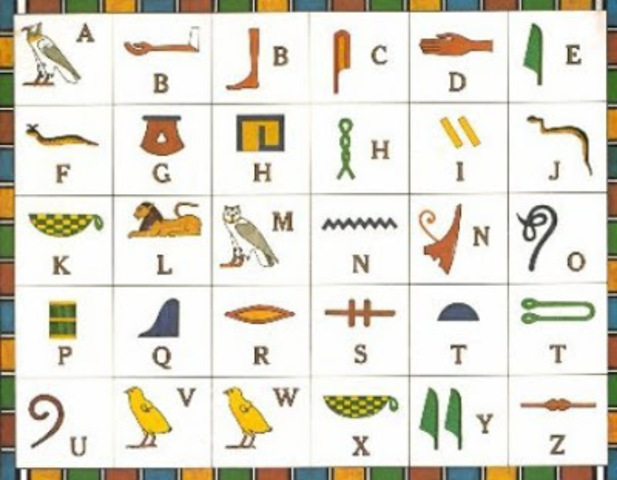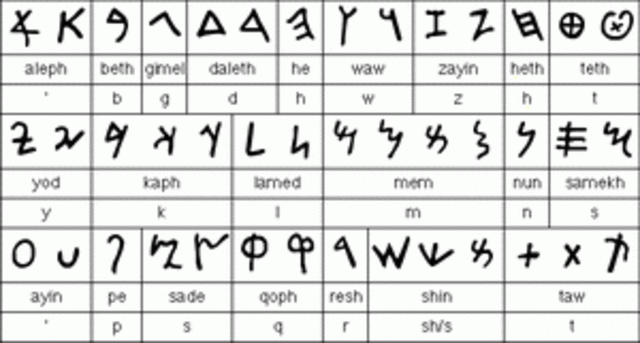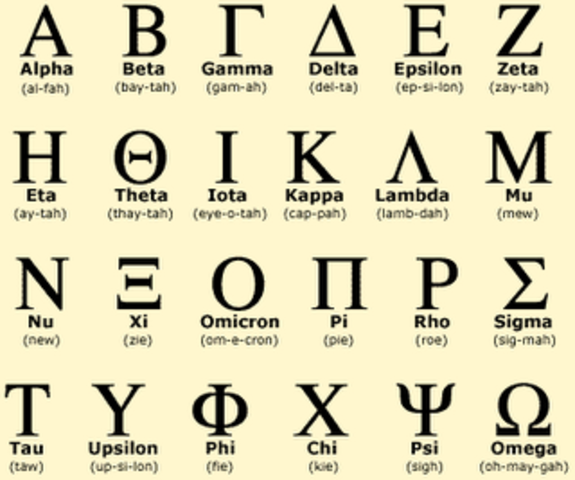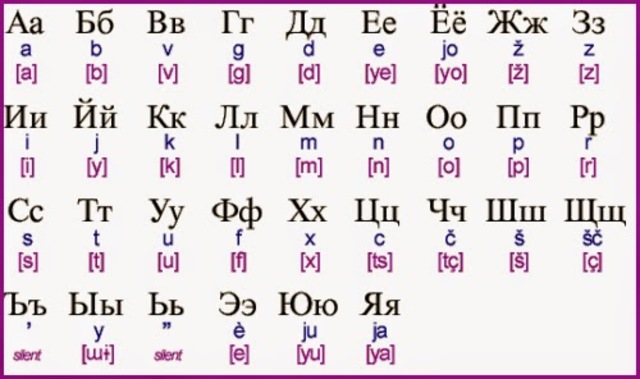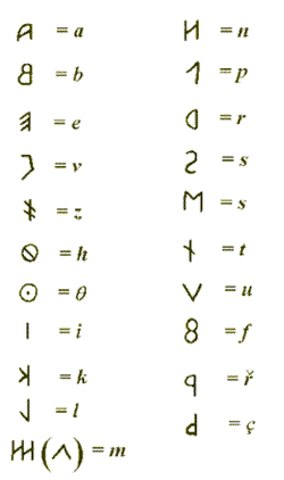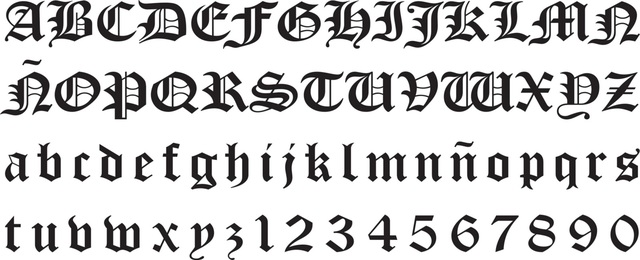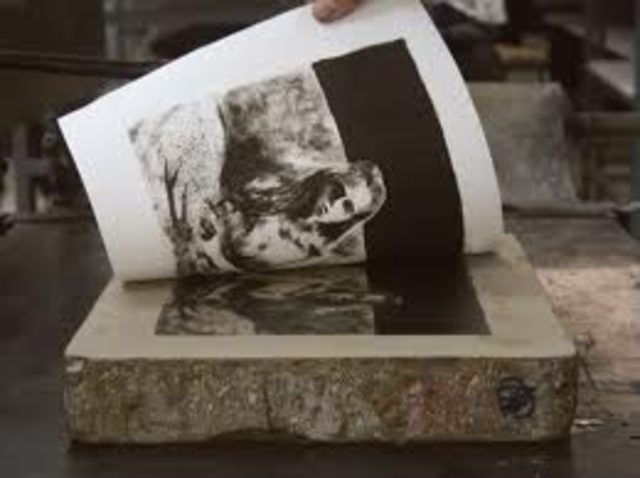
Se asigna un símbolo distintivo a cada palabra, se basa en palabras que expresaban conceptos abstractos con ideogramas que representaban sonidos en lugar de conceptos. una escritura estandarizada denominada "caligrafía del pequeño sello".
Adoptaron el los caracteres del sistema fenicio y lo utilizaron para desarrollar su propio alfabeto. se convertiría en la base para la escritura árabe y hebrea. se dio la introducción de los espacios y las vocales. utilizaron los espacios y signos diacríticos
Se formó a partir del alfabeto griego y se difundió por todo el imperio. los romanos utilizaban 7 de sus letras como números básicos.
consta de 26 letras con una base del alfabeto griego. entre estas se distinguen 7 letras como números básicos que representan un valor númerico combinado en bloques
El arameo evolucionó a partir del fenicio en el territorio de Siria y el sudeste de Turquía. El arameo es un idioma semítico que fue remplazado a finales del siglo VI a.c sustituido por la escritura hebrea cuadrada.
invento la primera imprenta se dio la producción de libros, con el uso de tipos móviles se podía reutilizar los caracteres del texto una forma de ahorrar dinero y tiempo que se hacia con una impresión metal caliente.
Los fundamentos del alfabeto latino actual, se formalizo un sistema de veintidós símbolos que representaban sonidos en lugar de objetos. estos símbolos se pueden combinar y entre si y construir miles de palabras, a pesar de que solo contenía consonantes y ninguna vocal. Dio origen al árabe, hebreo, griego, latín y el alfabeto europeo.
Su nombre se debe al misionero bizantino San Cirilo. constituye la base de más de 50 lenguas distintas en Rusia, asía central y el este de europa.
fusión del arte y la industria. se crean carteles y cromos en color para libros.
una barra metálica, se colocan matrices de latón en una linea y se realiza la fundición
Se basa en pictogramas, empleada por varias culturas incluidas los incas y los egipcios. cada pictograma representa un objecto, animal, herramienta o persona en lugar de un sonido vocal. los ideogramas indican una idea o concepto pero no indican como se pronuncian las palabras.
Considerado el primer sistema de escritura estandarizado, en la antigua Mesopotamia. se utilizada un estilete en forma de cuña para realizar marcas en una tabla de arcilla.
El alfabeto moderno esta compuesto por 52 letras y 10 números, varios símbolos, signos de puntuación, y acentos utilizados en las diferentes lenguas.